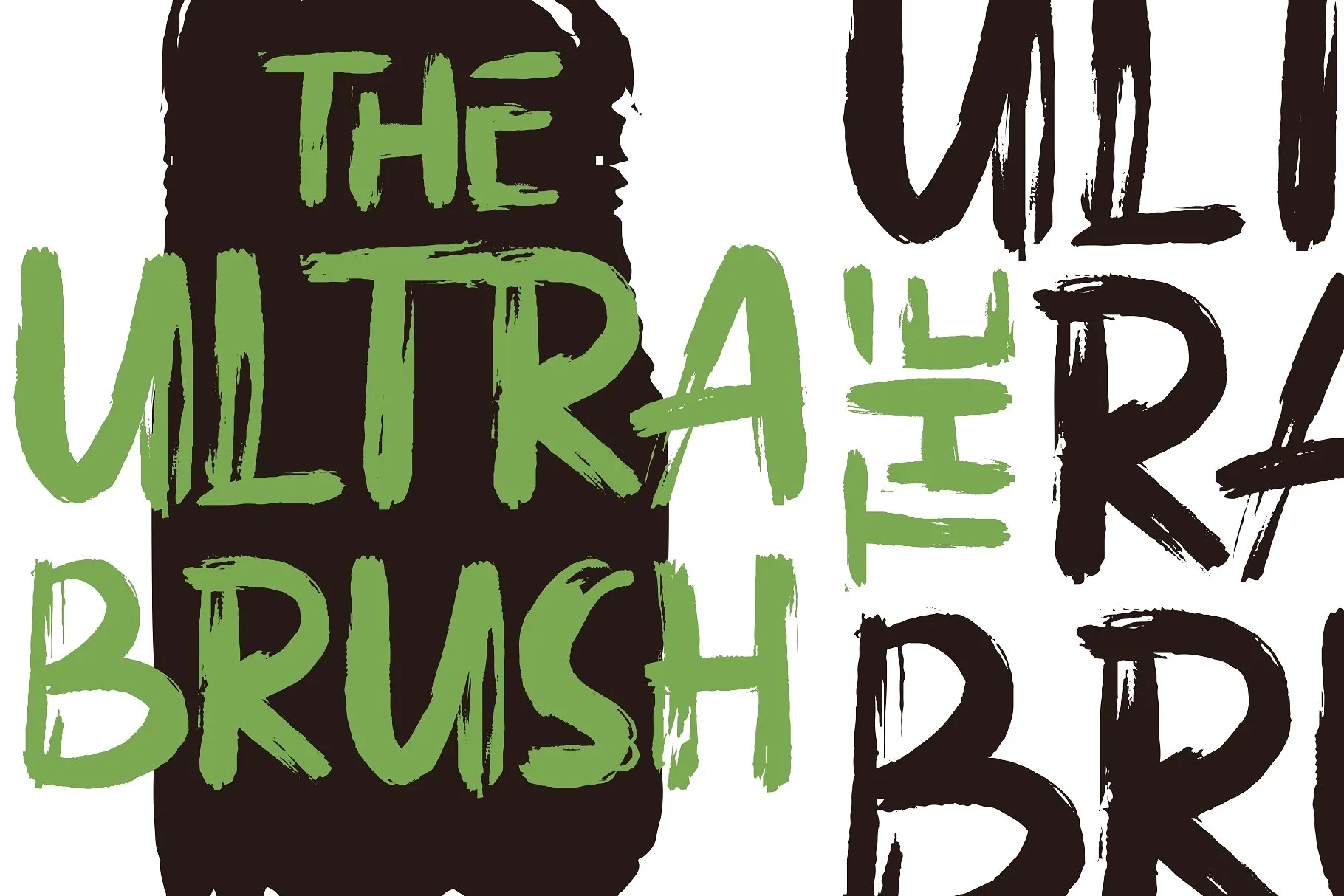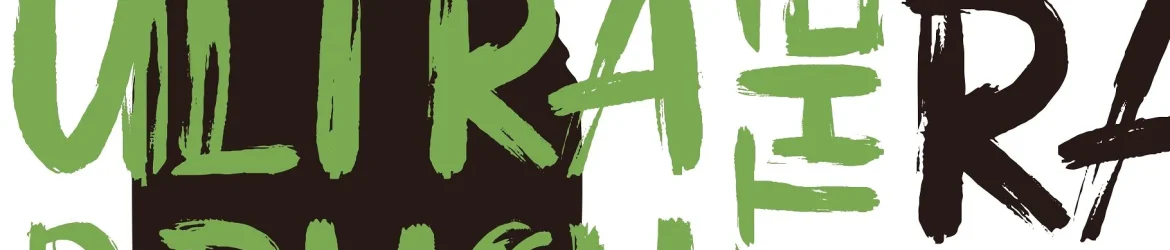
A fonte The Ultra Brush é uma opção ideal para designers que buscam versatilidade no seu trabalho. Essa fonte foi criada para atender aos mais diversos requisitos, sejam eles poster, camisetas com mensagens, marcações, embalagens e até mesmo logotipos. O designer zziplex utilizou uma ferramenta natural de esfumar como base, o que resultou na criação do Ultra Brush Font, projetada para atender às necessidades dos criadores de conteúdo visual. Esta fonte é perfeitamente adaptável a um amplo espectro de aplicações. Seja você designer gráfico, criador de conteúdos digitais ou mesmo alguém que deseja dar uma cara mais personalizada aos seus materiais impressos, o Ultra Brush Font oferece a solução. Com características naturais e um design intuitivo, é fácil trabalhar com ela para criar mensagens fortes e impactantes. A fonte The Ultra Brush é perfeita para quem está sempre em busca de inovação e criatividade na criação visual. Suas linhas dinâmicas e sua variedade de formas permitem que você crie uma variedade imensa de projetos, desde pequenas identidades digitais até grandes obras de arte de grande porte. O designer Garisman Std é o responsável pelo desenvolvimento e compartilhamento desta fonte original. Ao criar o Ultra Brush Font, ele atendeu ao interesse por desenhos em estilo brush que já estão presentes no mercado atual. Essa fonte foi feita para responder às demandas dos designers para criar materiais visuais impressionantes para uma variedade de tarefas. Com a The Ultra Brush Font, você pode tornar seus projetos ainda mais expressivos e profissionais. Seja na criação de um design minimalista ou uma peça com muita personalidade, esse é o recurso que você precisa para dar vida à sua ideia.